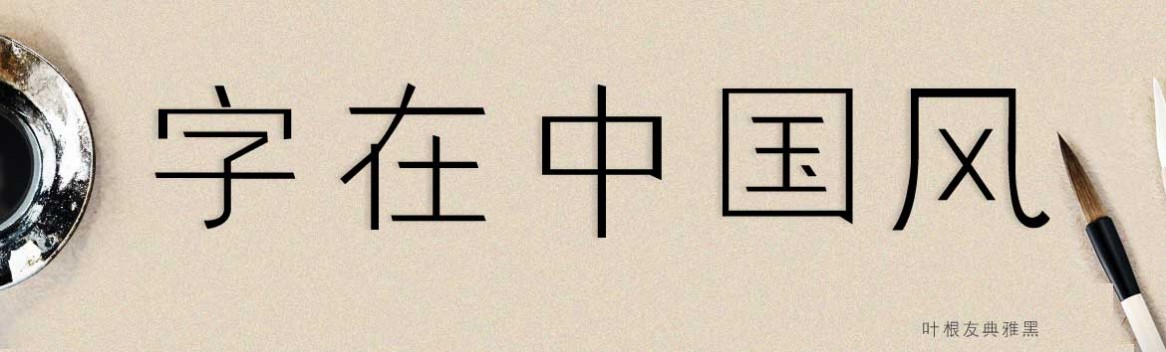
葉根友典雅黑
字體作者:葉根友
創(chuàng)作年代:2013年
字體字?jǐn)?shù):6763個(gè)中文漢字以及其他英文字母和阿拉伯?dāng)?shù)字
字體適合:內(nèi)文排版或手機(jī)應(yīng)用
字體介紹
葉根友典雅黑是一款正規(guī)的黑體類型的字體,是微黑字體的風(fēng)格借鑒版,字型干練利落,具有時(shí)代鮮明特點(diǎn),線條流動(dòng)韻律之書法風(fēng)格的美中透露出一種銳氣,起筆落筆間的15度斜角,讓字的展現(xiàn)更具時(shí)代特征,適合用于內(nèi)文排版字體。